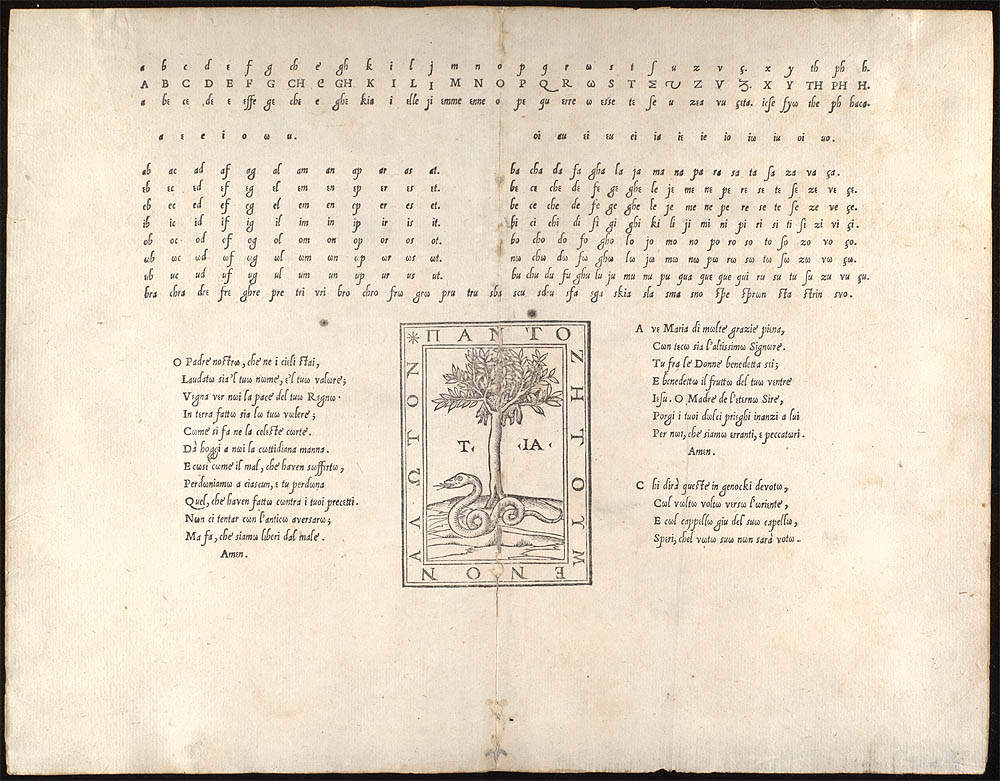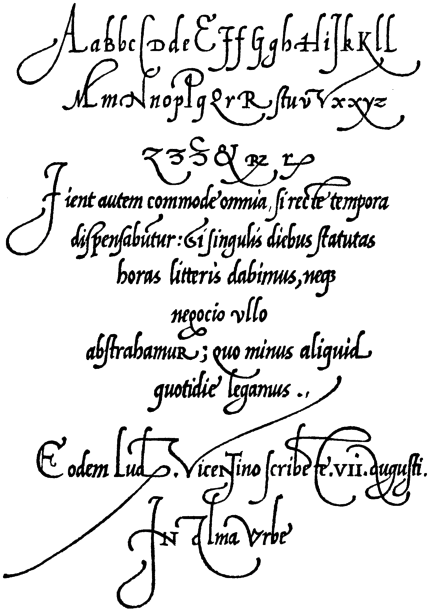
Ludovico Vicentino degli ArrighiLivreiro, editor, impressor, mestre-calígrafo e tratadista. Este autor de pelo menos seis letras chancelerescas teve influência na criação de tipos itálicos desenhados durante o século XVI.Ludovico Vicentino degli Arrighi (Vicenza, c. 1480 - 1527), foi escriba papal e um dos calígrafos que participaram na criação da cultura tipográfica ocidental durante o Renascimento italiano. Arrighi foi responsável pela popularização e difusão na Europa (através da sua Operina) do tipo específico de escrita cursiva chamado chanceleresco que se tornaria a nossa itálica. Ludovico Vincentino degli Arrighi foi assíduo colaborador de Aldus Manutius no desenho dos tipos móveis humanistas. Temporariamente foi membro do corpo de calígrafos da Curia Romana, a chancelaria papal.
Primeiro apareceu o seu famoso manual La operina em 1522 (1523?), e depois Il modo de Temperare le Penne, em 1525. Esta última obra foi produzida em associação com o gravador Eustachio Celebrino. A caligrafia cancellaresca italiana humanista, instituída por Niccolo Niccoli a partir da minúscula carolina, encontrou em Arrighi uma mão racionalizadora. A experiência de Arrighi em desenho tipográfico permitiu-lhe remover arcaísmos ainda presentes na caligrafia chanceleresca, reduzindo a letra a um modelo mais simples, claro e legível, facilmente executável por qualquer calígrafo. O Saco di Roma em 1527 pôs termo à carreira profissional e à vida de Arrighi. La Operina
Manual de Caligrafia de 1522, La Operina, a "obrazinha", é o primeiro manual de caligrafia impresso na era dos tipos móveis. Foi o responsável pela popularização da letra chamada chanceleresca, e por estabelecê-la como a cursiva preferida pela tipografia. Descrição do livro, em detalhe: http://briem.ismennt.is/ BibliografiaO historiador britânico Stanley Morison analisou com alguma profundidade a obra de A., assim como vários problemas relativos à qualidade e à datação das suas obras. FontesA Fundição digital P22 editou versões digitais da caligrafia de Arrighi: www.p22.com. Página actualizada em 02.2008